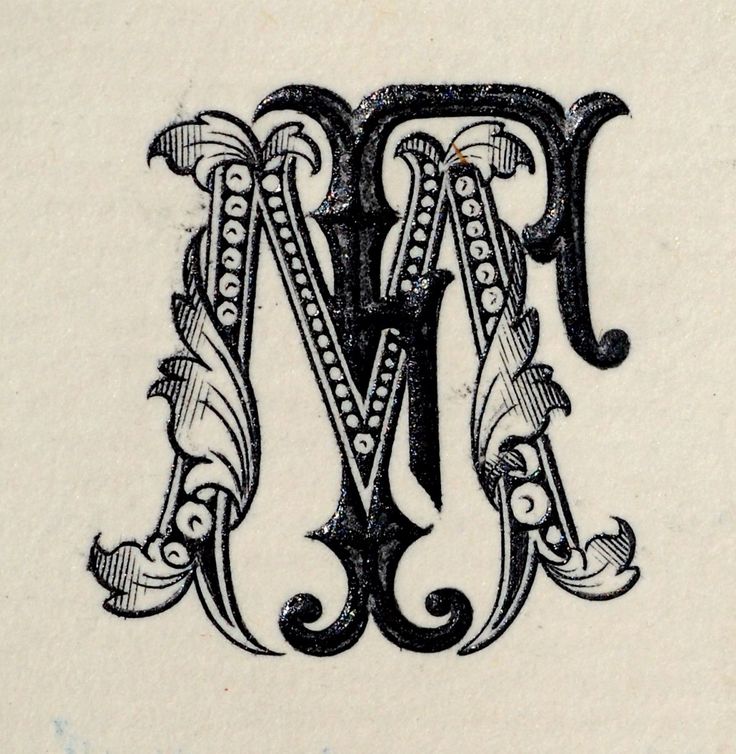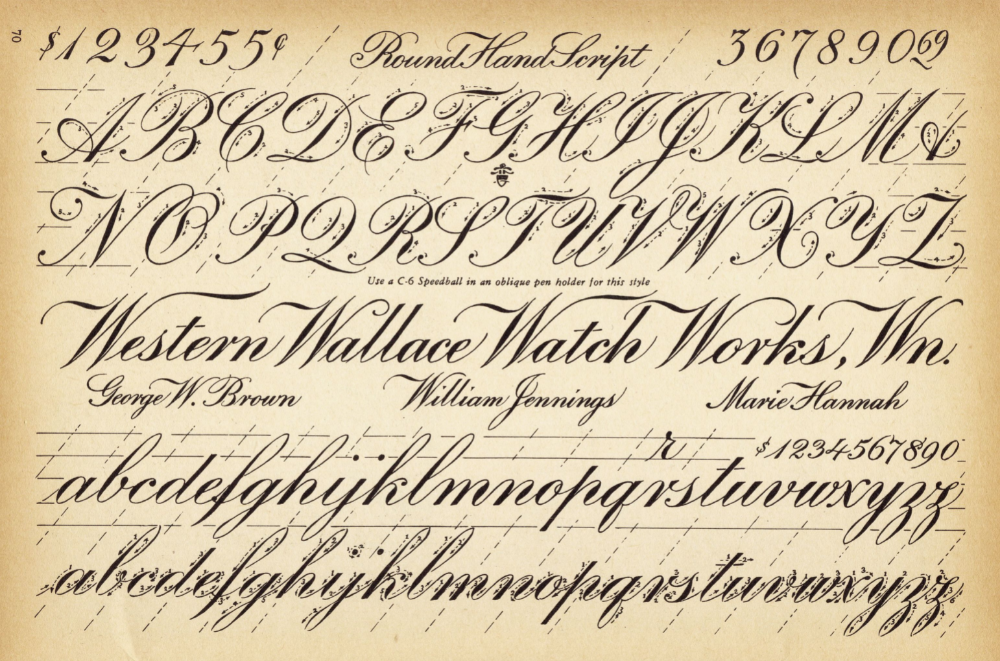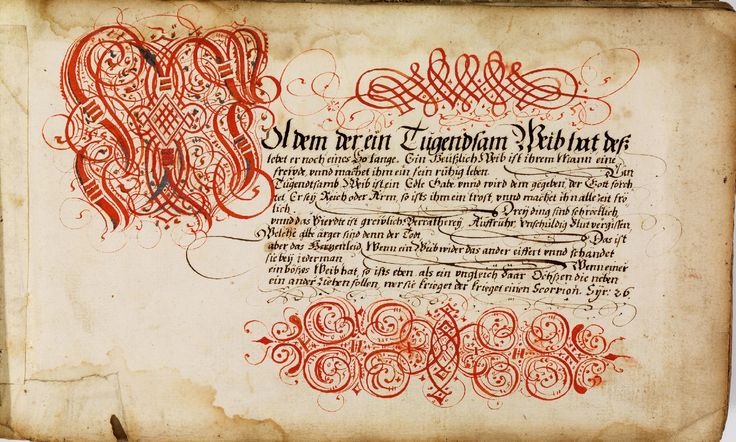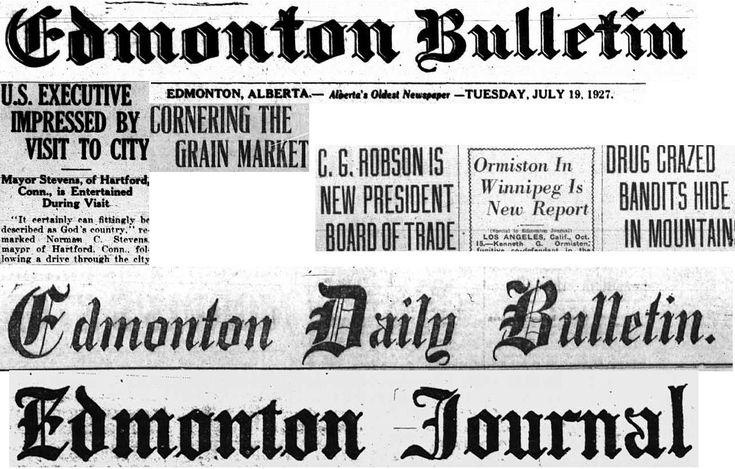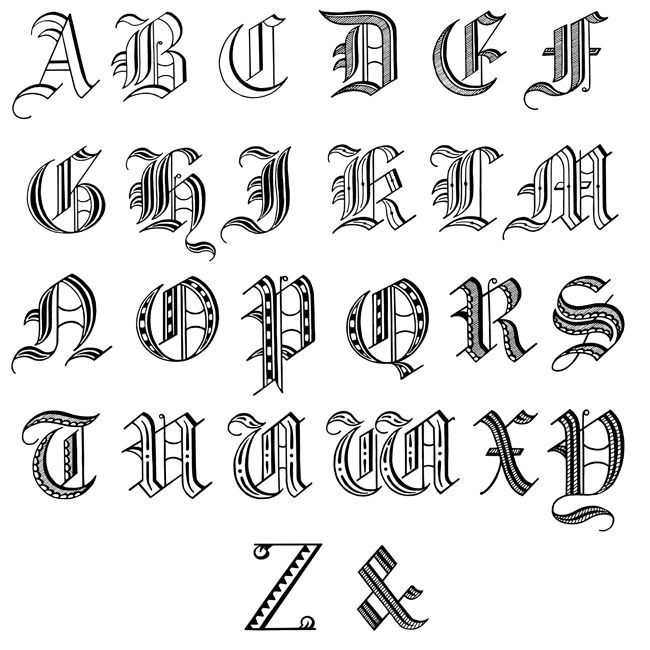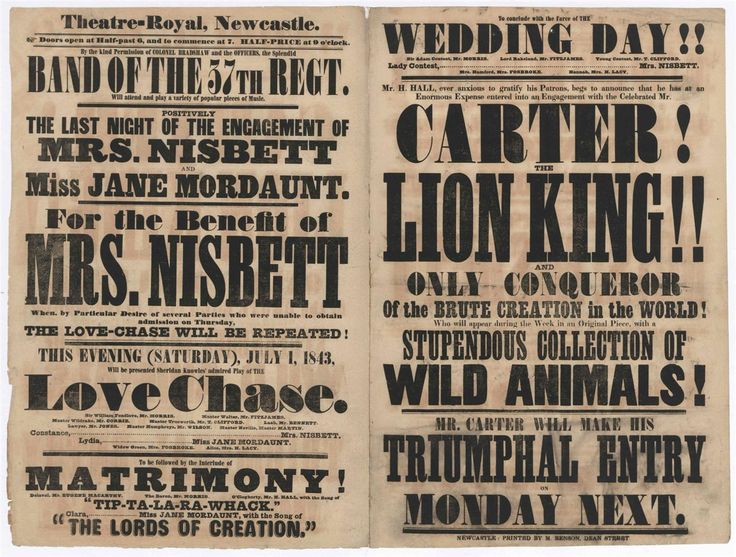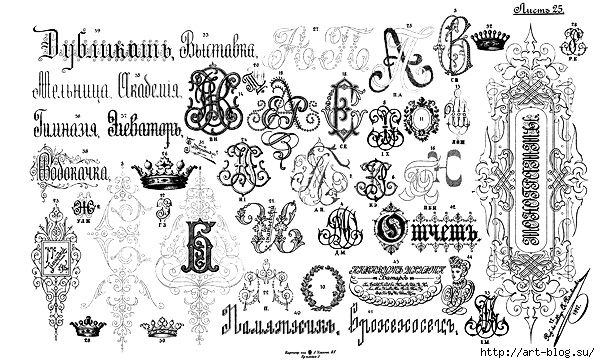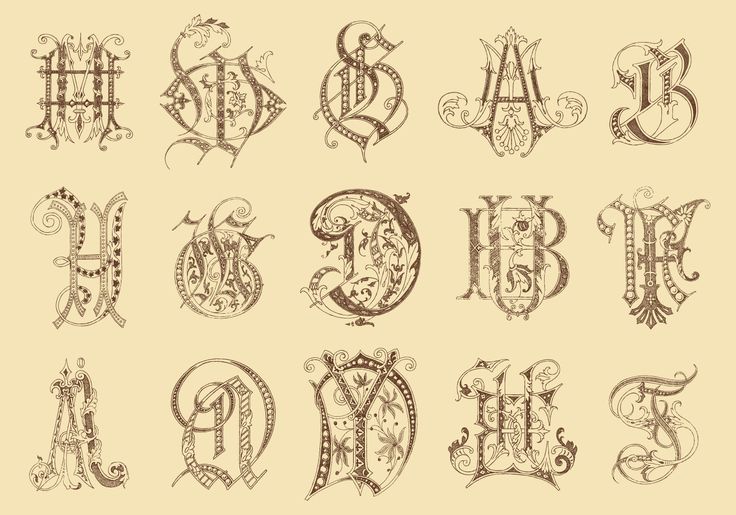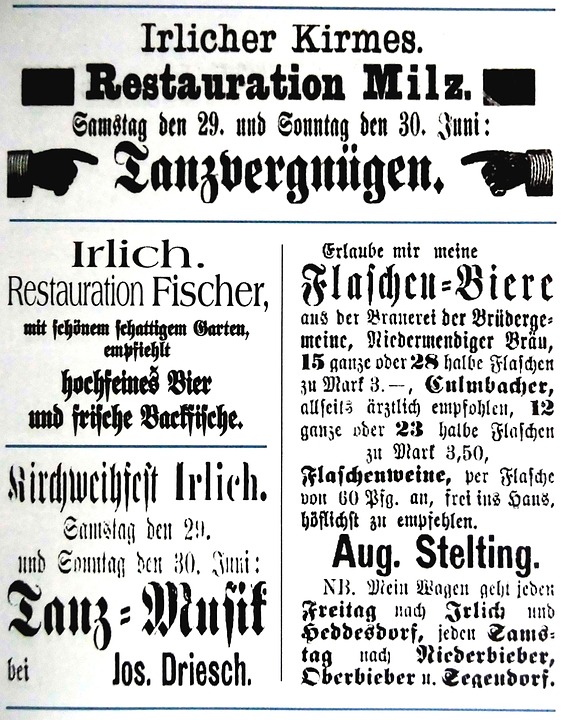
Лучшие ретро-шрифты для совершенствования вашего дизайнаDesigne-R
В этом посте мы представляем вам коллекцию высококачественных винтажных и лучших ретро-шрифтов, чтобы добавить нотку ностальгии в вашу работу.
При создании дизайна под влиянием искусства и культуры определенной эпохи лучше всего выбирать шрифты, которые визуально представляют этот период времени. Вот почему мы включили шрифты, вдохновленные эстетикой разных времен, будь то классический стиль начала 1900-х годов, стиль поп-арта 50-х и 60-х годов или фильмы, музыка и визуальные эффекты 70-х и 80-х годов. все!
Вы найдете сочетание различных стилей шрифтов, от шрифтов в стиле ретро до шрифтов кисти, жирных шрифтов с заглавными буквами до узких сжатых шрифтов, от монолинейных сценариев до многострочных шрифтов, пиксельных шрифтов, старинных шрифтов и многого другого.
Эти шрифты идеально подходят для ваших проектов в винтажном и ретро-стиле, таких как флаеры, баннеры, приглашения, футболки, плакаты и дизайн логотипов.
В нашей коллекции есть как бесплатные, так и платные шрифты, и мы поместили их в разные разделы для удобства просмотра. В последнее время в моде ретро-дизайн 80-х и 90-х годов, ниже вы найдете довольно хороший выбор шрифтов, на которые повлияли стили шрифтов этих знаковых десятилетий.
Бесплатные винтажные и ретро шрифты
1. Streetwear – Бесплатный ретро Script шрифт